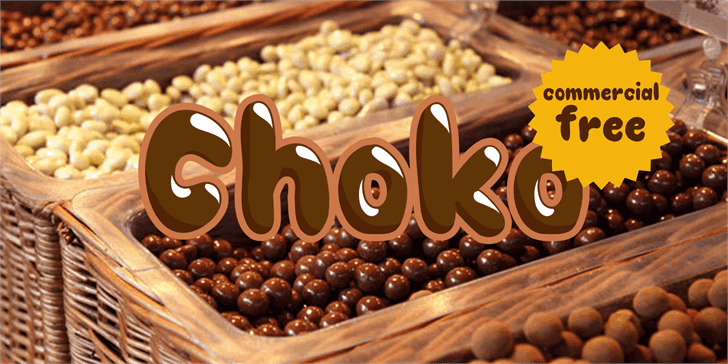
A fonte Choko foi criada por Måns Grebäck em 2011, mas permaneceu em segredo até 2016. Essa elegante e vibrante fonte é perfeita para aplicativos de design visual como logo criação, editoração de imagens ou ilustrações digitais. Com uma tipografia forte e única, Choko traz uma vibe moderna e sofisticada que certamente impressionará seus usuários. Através da sua família fonte, composta por diferentes pesos (from extra light a bold), você tem a liberdade de explorar infinitas possibilidades para tornar suas mensagens vibrantes e memoráveis. Choko é uma opção ideal tanto para designers profissionais quanto para aqueles que desejam adicionar um toque diferenciado à sua obra. Com certeza, Choko vai tornar seu design mais atraente e imponente.